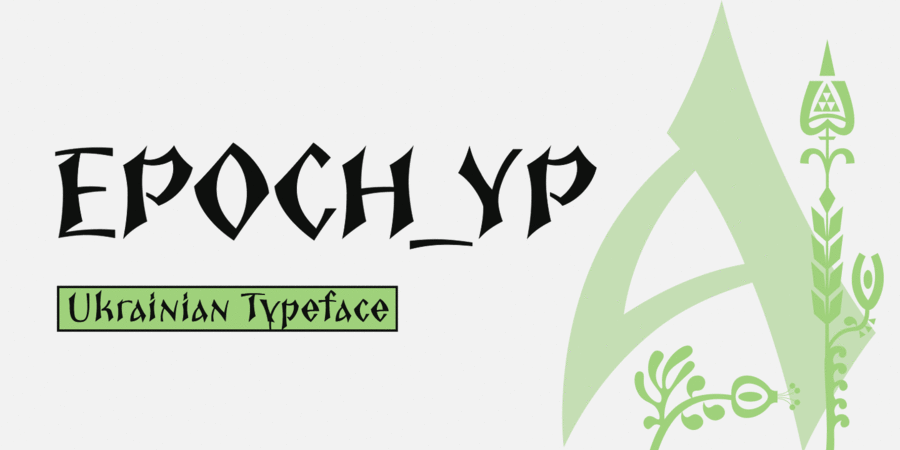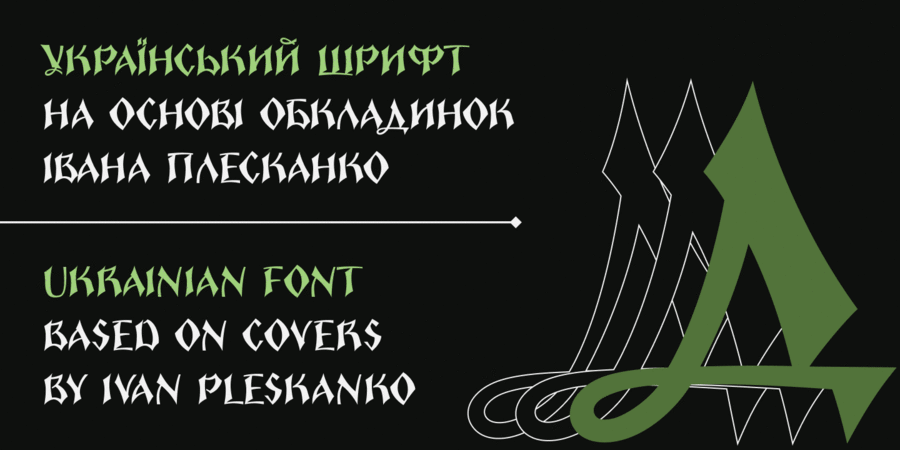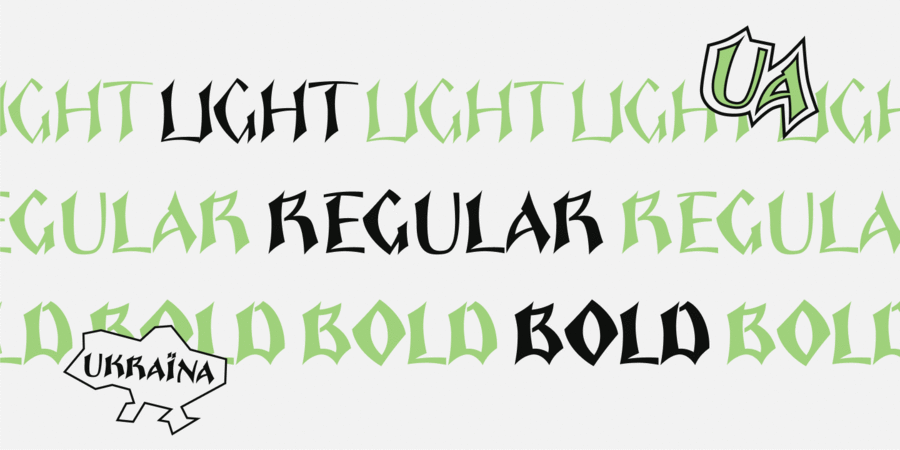
Епоха – це акцидентна гарнітура з динамічними формами, натхненна книжковою графікою художника Івана Плесканко та українськими шрифтовими традиціями ХХ століття. Шрифт поєднує декоративну виразність із функціональністю, завдяки чому може використовуватися в плакатах, обкладинках, етикетках і пакуванні, підкреслюючи українську культурну ідентичність дизайну.
В комплекті 1 варіативний шрифт зі змінною вагою, статичні накреслення Light, Regular, Bold та 1 безкоштовний шрифт Epoch YP Demo. Безкоштовна ліцензія – в архіві зі шрифтом. Шрифт підтримує українську кирилицю та базову латинку. Авторка — Юлія Передерій, 2025 рік випуску. Світ ловив мене, та не спіймав!